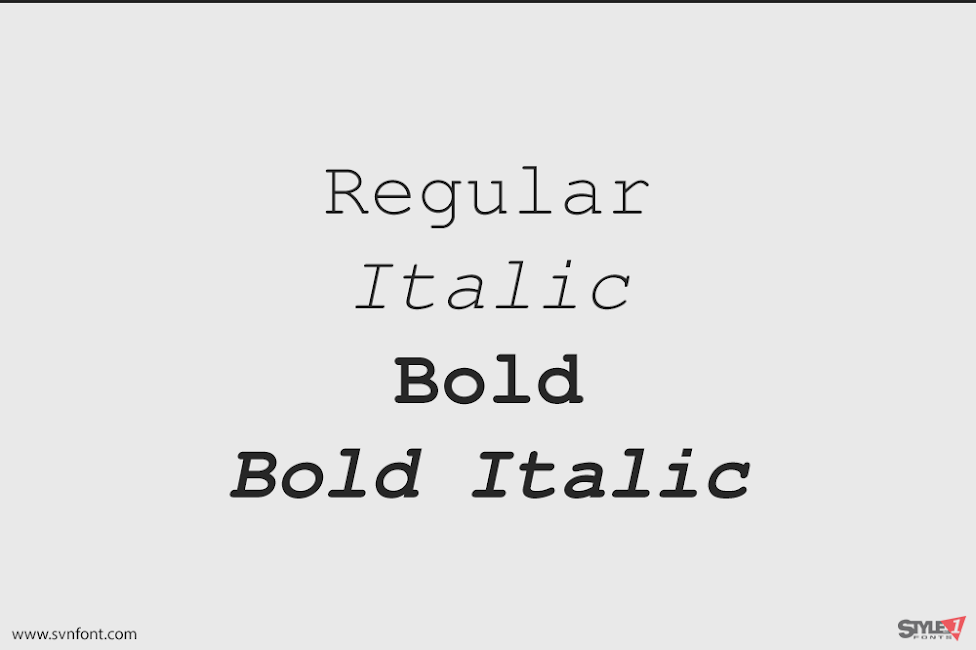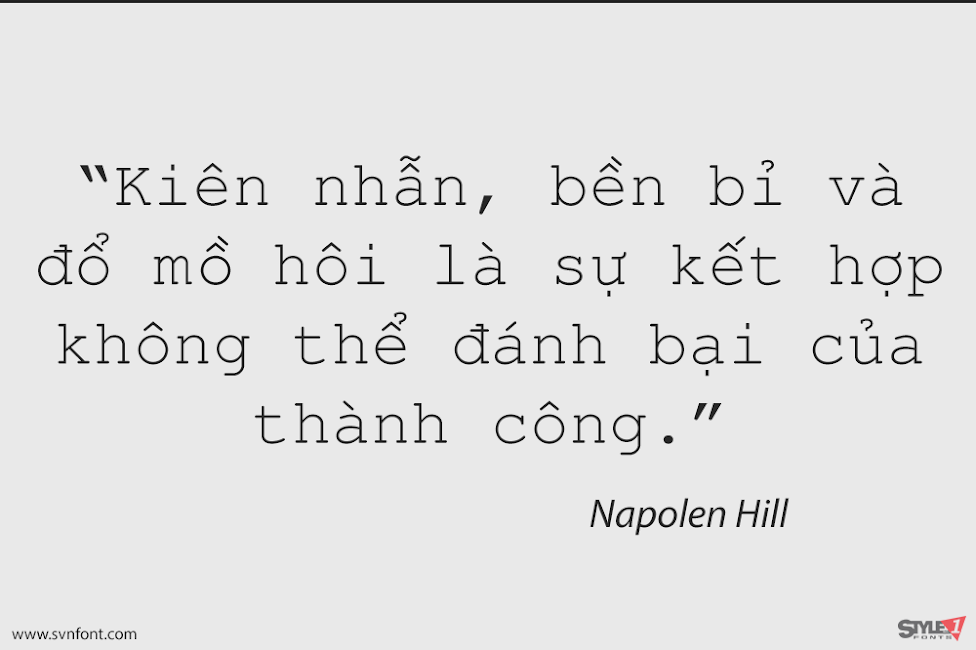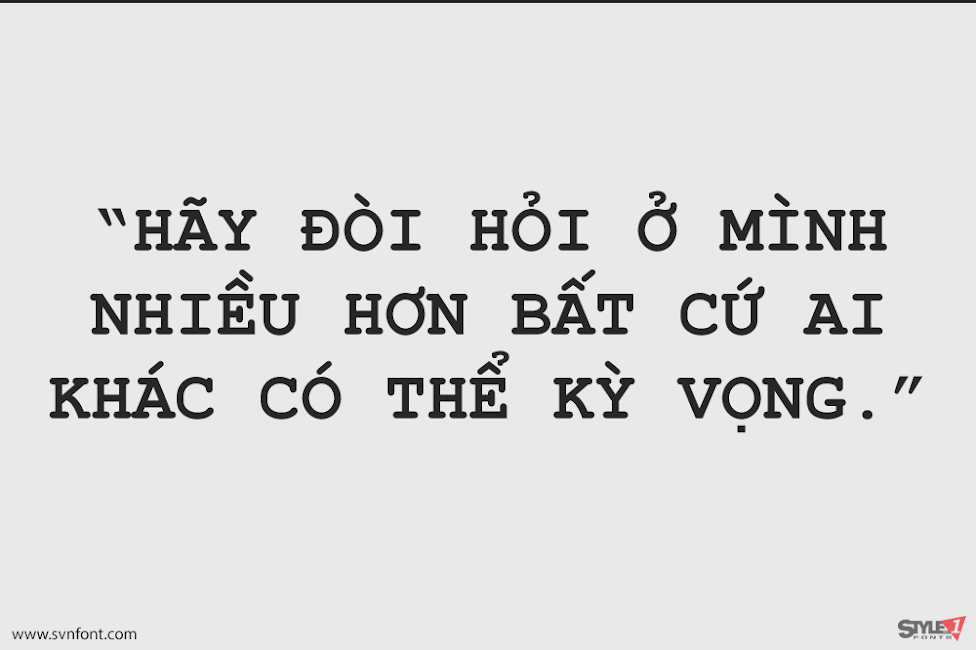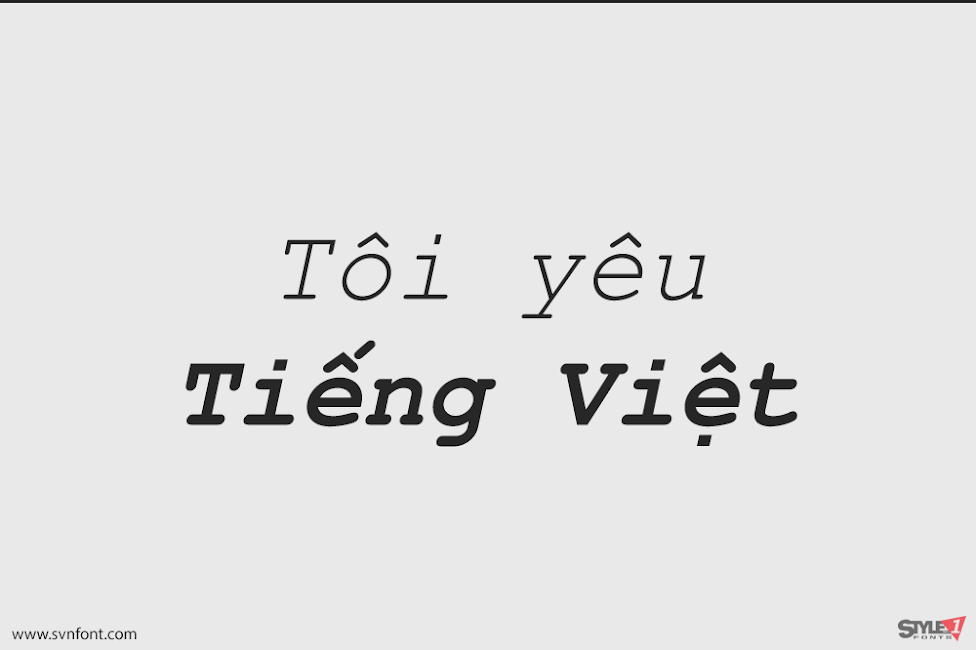
Nimbus Mono là một kiểu chữ đơn cách (monospaced) được tạo bởi URW Studio vào năm 1984, và sau đó được phát hành theo giấy phép GPL và AFPL (dưới dạng font Type 1 cho Ghostscript) vào năm 1996, và LPPL vào năm 2009. Nó có các độ dày Normal, Bold, Italic và Bold Italic, đồng thời là một trong số các font được cấp phép tự do bởi URW++. Mặc dù các ký tự không hoàn toàn giống nhau, nhưng Nimbus Mono có các thông số kỹ thuật (metrics) rất tương tự với Courier và Courier New.
Nhà thiết kế: (URW)++